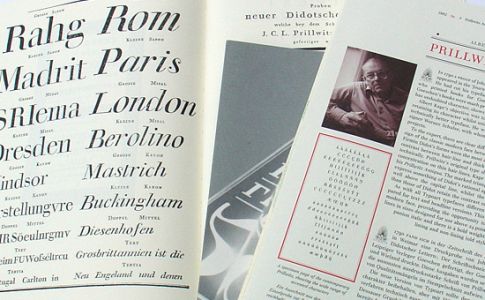
Hab am Wochenende gut 70 Schriftmuster-Bildchen ins Wiki geladen:
[wiki]Typoart[/wiki]
Wenn jemand noch ein paar Beschreibungstexte beisteuern könnte, wäre das toll. Andreass hat sich ja zum Beispiel nun als Thannhaeuser-Experte geoutet. :wink:
Bei allem Respekt:
Wenn man so gar nichts besseres hat, dann ist das Wort "Hamburg(er)" oder ein anderes Musterwort bzw. -satz natürlich ganz niedlich und besser als gar nix.
Sinn macht so etwas aber tatsächlich erst, wenn ein kompletter Zeichensatz abgebildet wird. :
Erler-Versalien:
Fundamental-Grotesk fett:
Pergamon-Antiqua:
auch Super-Grotesk und TypoArt Garamond kursiv, um nur einige zu nennen. Es geht mir jetzt wirklich nicht um "Meine sind toller.", bitte verstehe es als Anregung.
Was ich bei Deinem Eintrag dort sehr schön finde, ist die Nennung von vorhandenen digitalen Versionen. Das würde ich auch gern machen. Aber dazu fehlen mir Kenntnisse und die Zeit, um mir die anzueignen.
Da sind die Geschmäcker vielleicht auch verschieden. Als Schrift-Anwender ist mir eine Probefahrt viel lieber, als mir die Einzelteile des Wagens aufgereiht anzuschauen.
ralf ist es sicher etwas schwer gefallen seine schriftmuster anzudrucken
bzw. zu zerschneiden. ;) ich finde einen gesamtüberblick über alle buchstaben
genauso nützlich wie einen blindtext.
ich bin gerade mal ins archiv gestiegen, also
Timeless, Prillwitz, Magna, Primus, Minima, Publica
habe ich da.
außerdem fehlen noch:
· Schmalfette Antiqua (Barbara Cain)
· Fette Antiqua (Barbara Cain)
· Norma Steinschrif (Harald Brödel)
hat das was mit der steinschrift von herrn Preuß zu tun?
· Egyptienne (Hans-Peter Greinke)
· Nidor (Harald Brödel)
· Eckmann (Werner Schulze)
· Publica (Karl-Heinz Lange)
· Kleopatra (Erhard Kaiser)
· Zyklop (Fritz Kossack)
· Quadro (Erhard Kaiser)
· Biga (Fritz Richter)
· Molli (Harald Brödel)
· Hogarth Script (Harald Brödel)
· Luthersche Fraktur (Volker Küster, Herbert Lemme)
· Caslon Gotisch (Erhard Kaiser)
· Schwabacher (Herbert Lemme)
· Marko (Hausschnitt ohne Angaben, Erstguß 1920)
· Thannhaeuser Initialen (H. Thannhaeuser)
· Meister Kursiv Initialen (H. Thannhaeuser)
das sind zum großteil fotosatzschriften von typoart, bzw. übernommen und
überarbeitete schriften von schelter & giesecke. in wie weit diese zu designer
zu typoart zählten und ob die schriften wirklich erhältlich waren weiss
ich nicht. ich habe sie aus dem buch fotosatz schriften von kapr.
bei den Schriften Splendor, Thomas Schrift (Versalien), Sinkwitz Versalien,
Agitator, Impuls, Kurier, Polo und Arabella-Favorit ist auch kein muster
hinterlegt, hätte ich ggf. auch.
Drescher Eilschrift (von Arno Drescher?)
Blocksignal (Signal)
Reporter
Knock out
Gnom
eine Sütterlin
Rautendelein Tausenschön
Cornelia
Mendelssohn
Holla
Jochheim (eine Schaftstielfgrotesk)
Fanal
Claudius
Patria
Derby
Schreibmaschinenschrift
Edel Grotesk
Ultra
Perkeo
Akropolis
Neon
Umbra
Prisma
Maxima
Lucina
Koralle
habe ich noch auf schriftmusterkarteikarten (1963) von dem
Karl-Marx-Werk Pößneck gefunden. in wie weit das typoart-schriften
sind weiss ich auch nicht. einige davon sind mir bekannt andere habe
ich noch nie gesehen. leider habe ich als muster davon nicht mehr
zeichen als der name der jeweiligen schrift.
war in dem Zusammenhang ungeschickt plaziert,
das zeitgleiche Aufzeigen der Typoart-Prillwitz reiner Zufall.
»Die Preusstype-Prillwitz vermittelt den Geist der Originale wirklich hervorragend.«
Dieser Einschätzung würde ich mich gerne, ohne leider die Originaldrucke zu kennen, anschließen.
Oberflächlich verglichen hatte ich aber schon (siehe Angeber-Beweisbild).